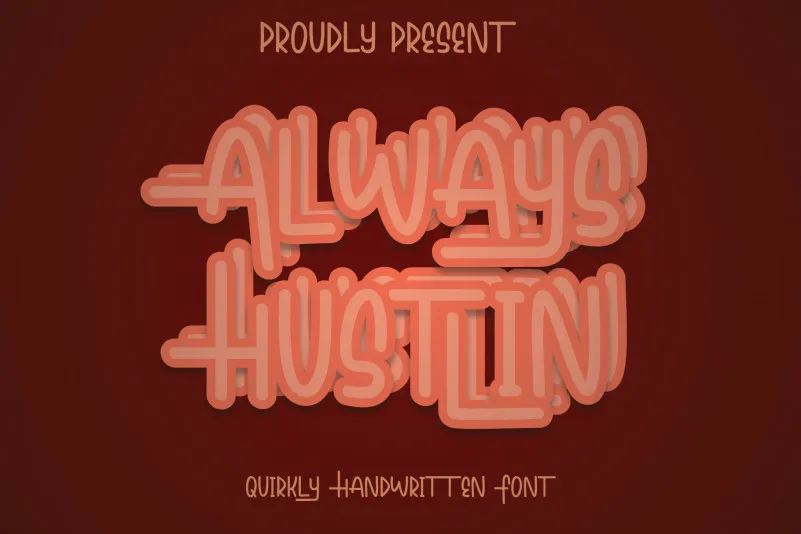
A fonte ‘Always Hustlin’ é uma opção irresistível para aqueles que buscam um visual moderno e chamativo. Desenvolvida pelo designer Erik Studio, esta fonte é perfeitamente adaptável para aplicação em materiais impressos como posteres, cartazes ou qualquer outro projeto gráfico onde você precisa de um design poderoso e fácil de ler. O seu formato display garante que a ‘Always Hustlin’ se destaque na tela ou no papel, tornando-se uma escolha ideal para expressar uma mensagem forte e vibrante. Com seus traços definidos e modernos, essa fonte oferece inúmeras possibilidades criativas, permitindo-lhe explorar seu potencial enquanto trabalha em projetos de design gráfico. Sem dúvida, ‘Always Hustlin’ é a escolha perfeita para quem busca uma fonte de destaque e versátil para qualquer ocasião.